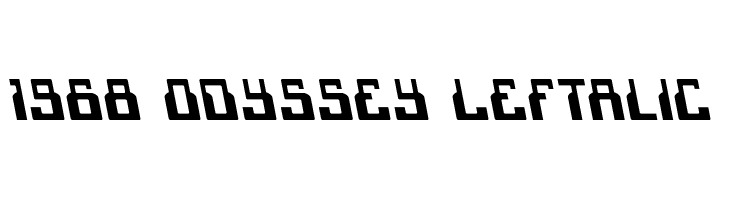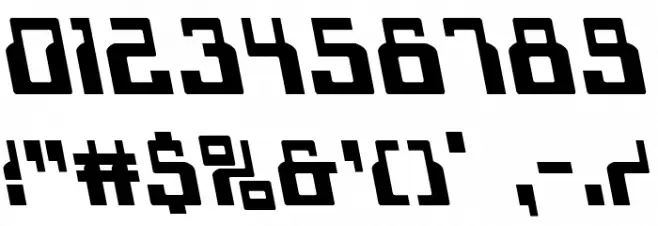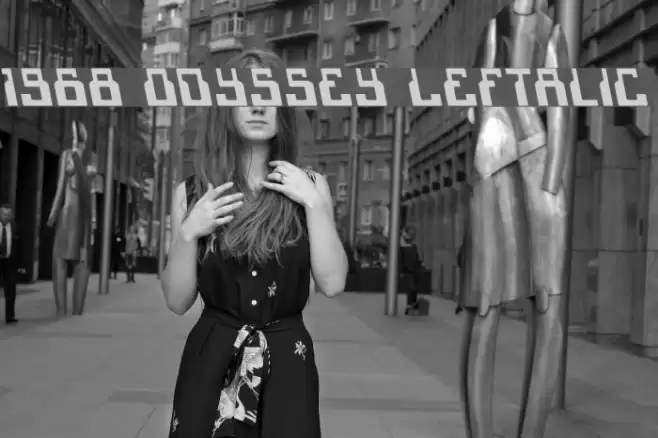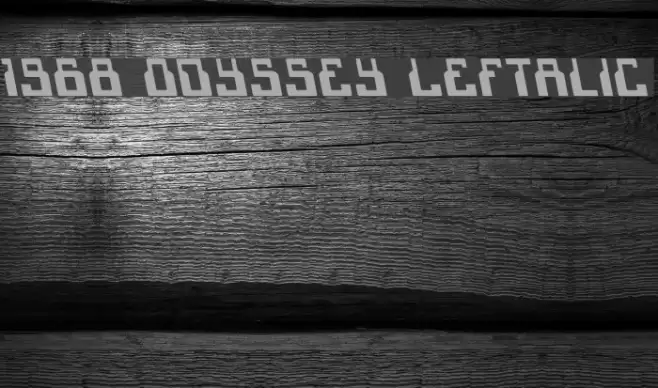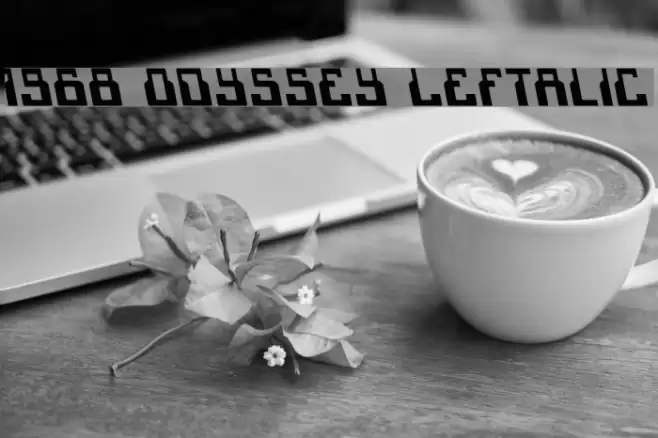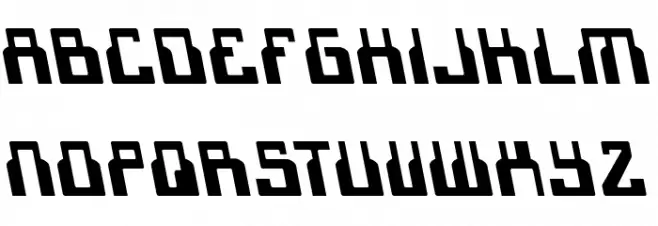
1968 Odyssey Leftalic Font
Fonts by Iconian Fonts
| 分类 | Futuristic |
| 整体风格 | Futuristic |
| 推荐项目 | Ideal for sci-fi themed projects, tech branding, video game titles, and futuristic posters. |